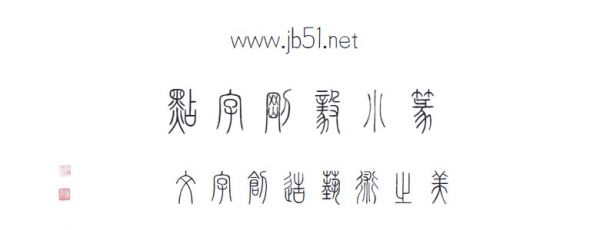
點(diǎn)字剛毅小篆是由點(diǎn)字庫(kù)推出的藝術(shù)字體,字體結(jié)構(gòu)嚴(yán)謹(jǐn),用筆中正從容,適合應(yīng)用于藝術(shù)設(shè)計(jì)、各類廣告和產(chǎn)品包裝設(shè)計(jì)等領(lǐng)域。
這款字體結(jié)構(gòu)嚴(yán)謹(jǐn),用筆中正從容。作者參照了《說(shuō)文解字》、《康熙字典》、《漢和辭典》等諸多篆書典籍,結(jié)構(gòu)規(guī)范,筆畫分明、結(jié)體順暢自然。